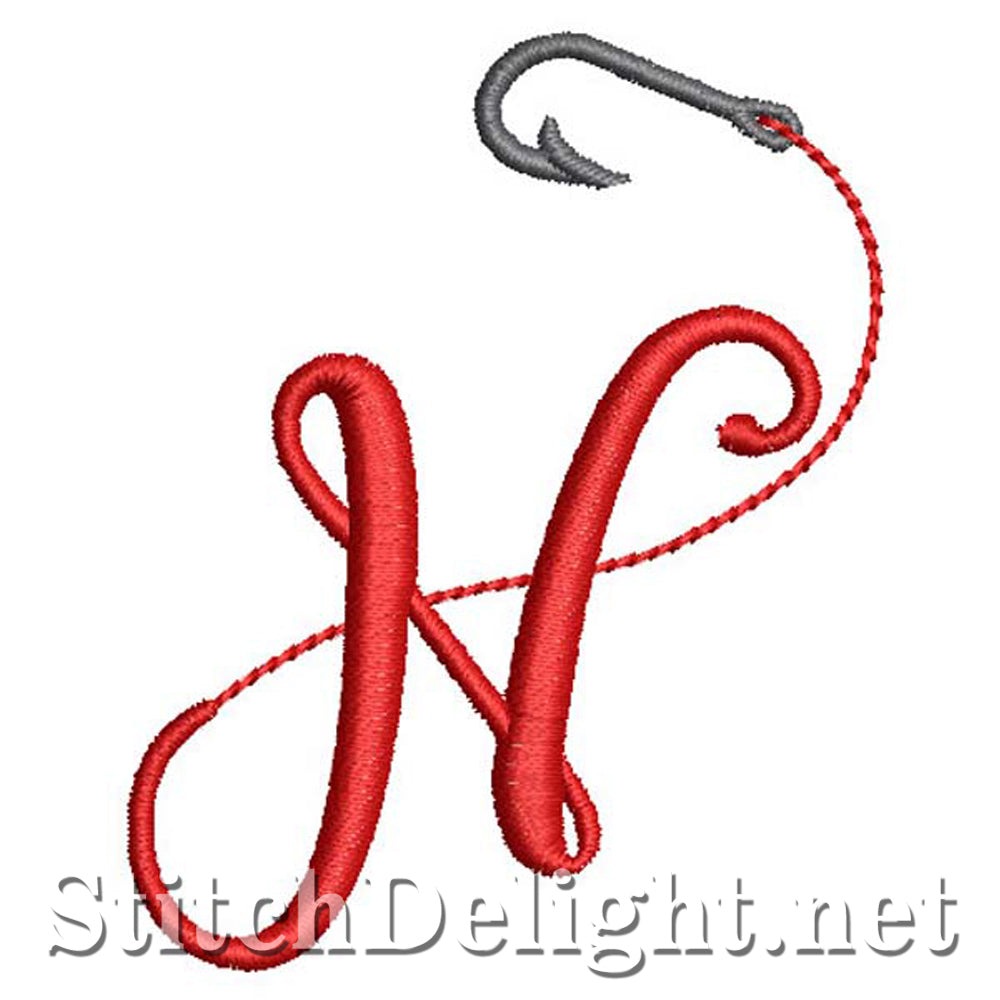
SDS1272 Police Fishline N
Devenez accro avec cette superbe police de pêche parfaite pour marquer vos chemises, vestes, chapeaux et équipements de pêche. Cette police a une hauteur moyenne de 3"